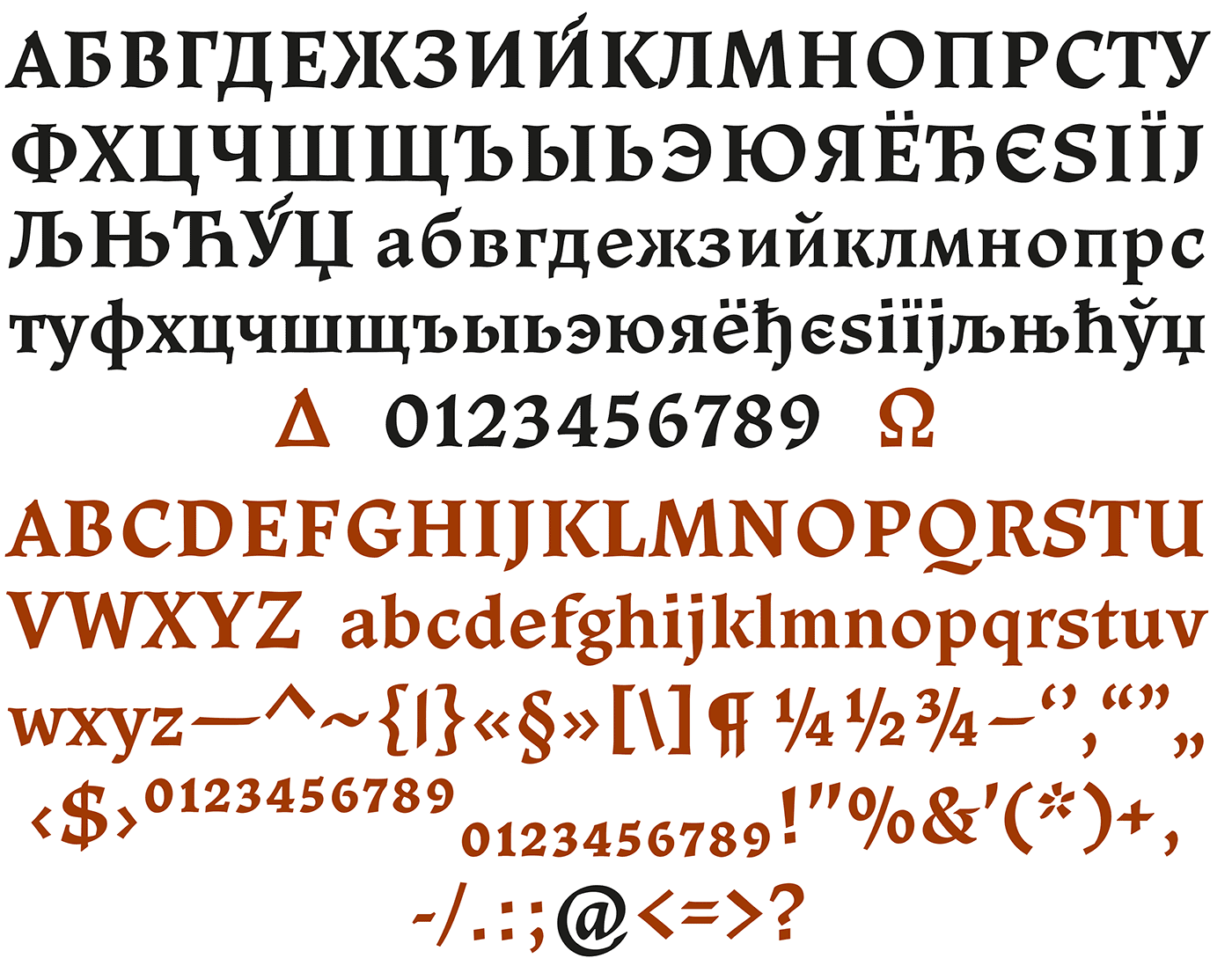
- 1968
- Antiqua humanistisch
Die Ladoga gilt als eine der wichtigsten russischen Schriftgestaltungen der Sowjetzeit. Sie wurde ursprünglich 1968 von Anatoli Wladimirowitsch Schtschukin für Polygraphmash gezeichnet, der versuchte, eine kyrillische Werkschrift im Stile der Renaissance-Antiqua umzusetzen. Die Nutzung der breiten Federstriche und großzügigen Proportionen humanistischer Minuskeln verleihen der Schrift ihren luftigen Charme.
2010 wurde die Schrift von Viktor Charik digitalisiert und ist seitdem bei Paratype in den Schnitten Kursiv und Recta sowohl als Display- als auch Textschrift erwerbbar. Seit 2013 wird die Schrift überarbeitet und auch als fetter Schnitt angeboten, jedoch noch nicht in der reichhaltigen Fassung von 2010 was die Sprachen, (historisches) Kyrillisch, polytonisches Griechisch, Hebräisch mit vielen masoretischen Vokalisationen anbelangt. Dafür ist die neue Fassung auch als Webfont erhältlich.,